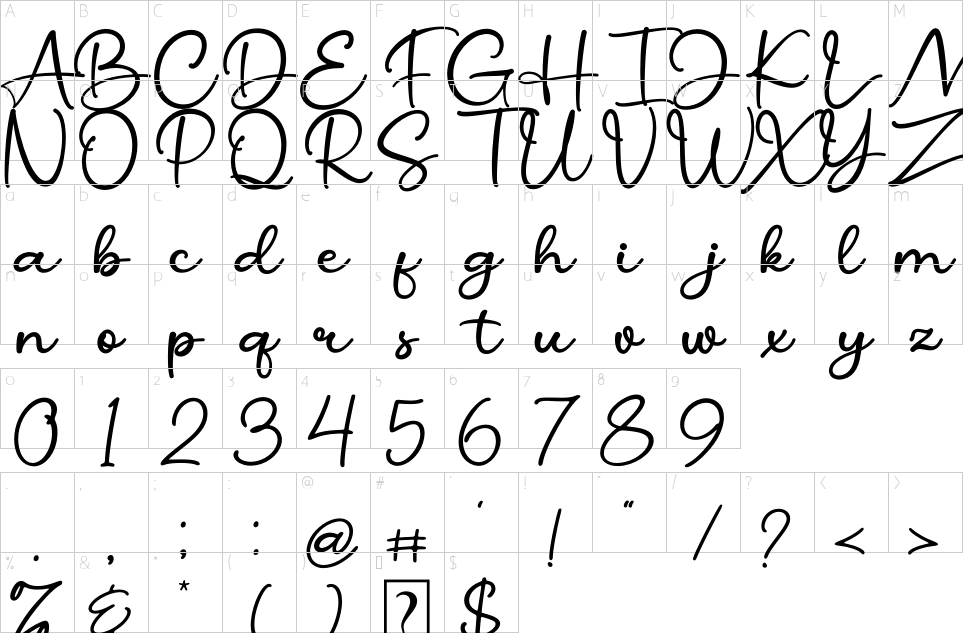
Millatira é uma fonte gráfica elegante e versátil que surgiu da imaginação criativa do Basnistudio. Seu design fluido e sofisticado, adequado para textos profissionais, fazê-la uma opção popular entre designers de todos os níveis. Millatira foi projetada para complementar a natureza e a harmonia do design gráfico moderno. A fonte já foi baixada 200 vezes, o que mostra a sua popularidade e qualidade. A Millatira é uma excelente escolha para qualquer projeto que precisa de um ar de sofisticação e elegância, seja para aplicativos, sites ou materiais impressos. Com seu estilo único, Millatira traz um toque agradável a qualquer projeto. Se você está procurando por uma fonte elegante e versátil para suas necessidades de design, a Millatira pode ser a escolha perfeita.